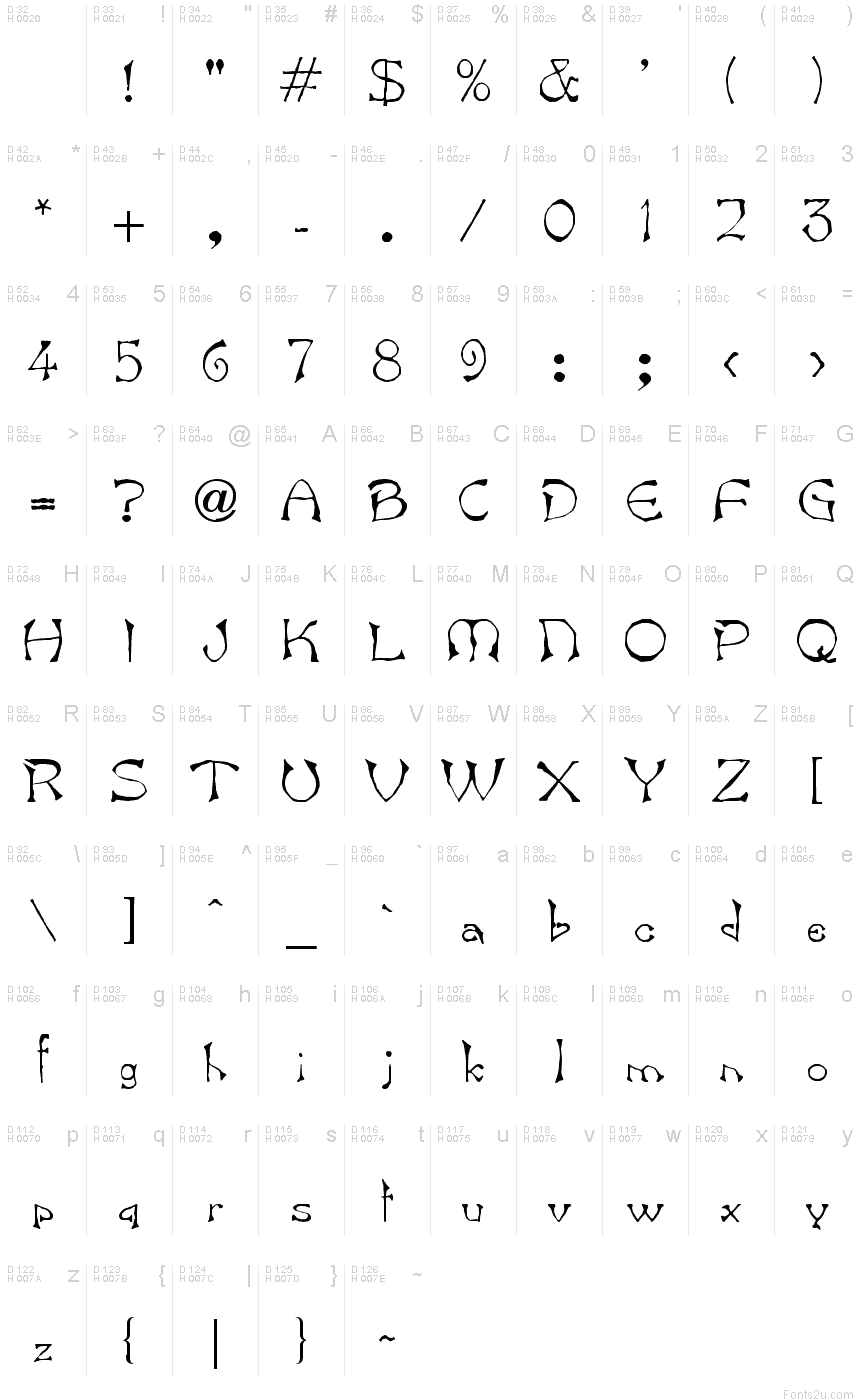
Krój pisma Bart od Bay Animation to darmowy, ręcznie rysowany font z poszarpanymi, atramentowymi liniami, które wyglądają, jakby zostały wydrapane na pergaminie. Nierówne krzywe, przekrzywione piony i lekko chaotyczny rytm nadają mu mroczny, baśniowy klimat, który natychmiast przywodzi na myśl tajemnicę, fantasy lub zjawiska nadprzyrodzone, nie sprawiając przy tym wrażenia przesadzonego.
Dzięki Bart Twoje nagłówki zyskują surowy, klimatyczny wyraz, który świetnie sprawdzi się na okładkach książek fantasy, gotyckich plakatach, ulotkach horrorów, logotypach gier indie, w brandingu escape roomów czy okultystycznych zinach. Ten darmowy font najlepiej prezentuje się w większych rozmiarach, gdzie jego nieregularne kontury mogą w pełni wybrzmieć. W mniejszym tekście łącz go z czystym krojem bezszeryfowym, aby zachować czytelność i równowagę układu.